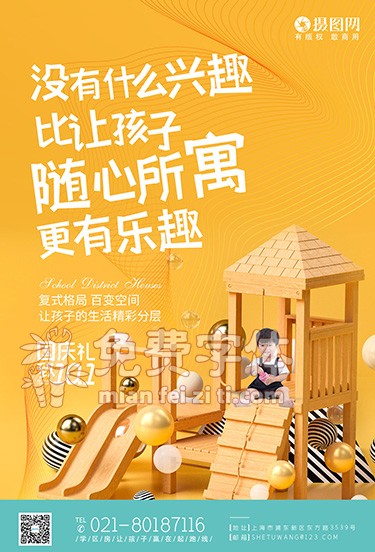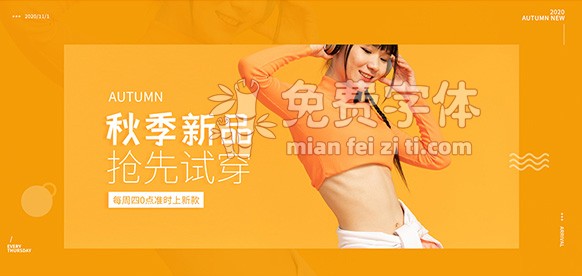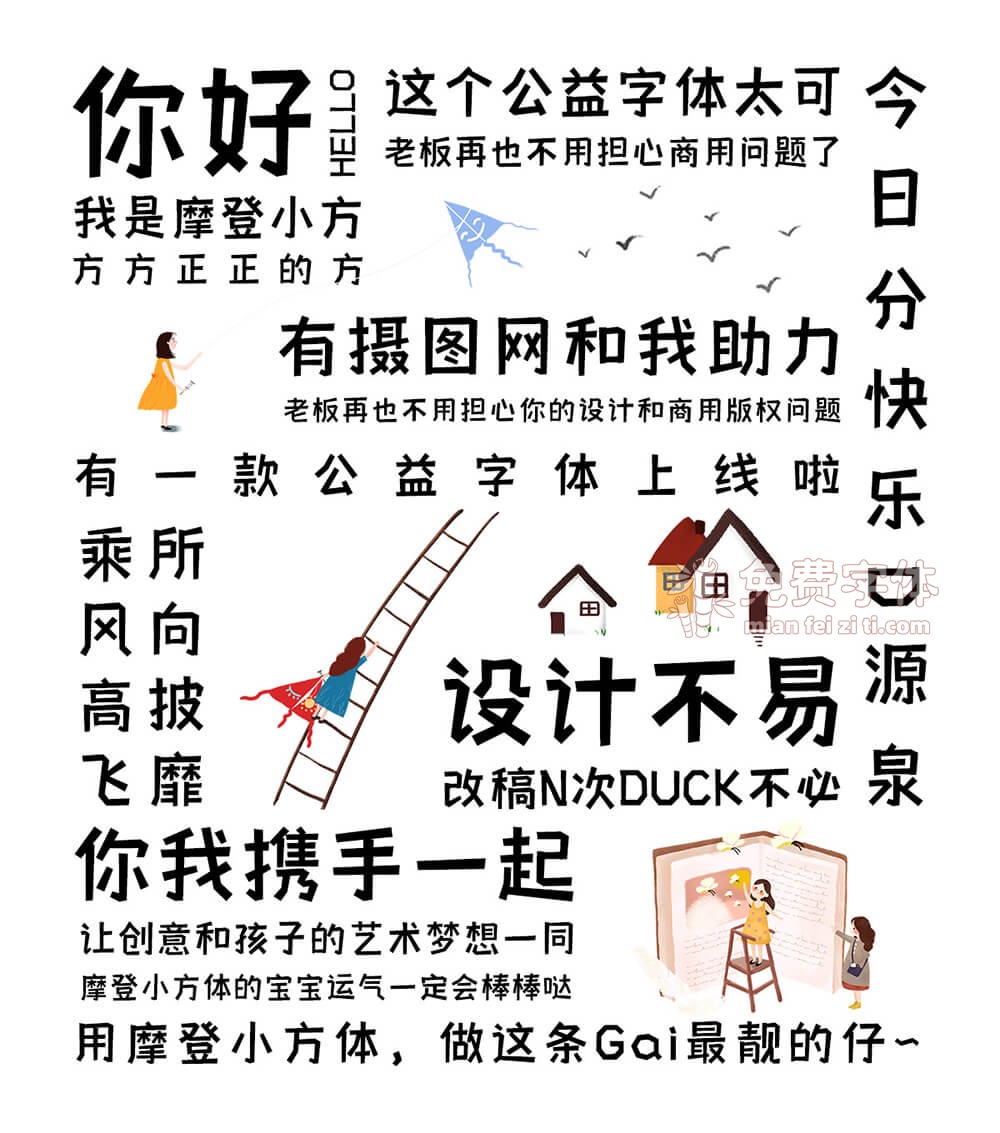
摄图摩登小方体是摄图网联合国内专业字体设计机构iFonts共同推出的一款公益创意黑体字。摄图摩登小方体作为一款创意黑体字,字体的设计灵感来自对未来空间的想象,传达给人一种未来与现实的交际感。笔画方正质朴而又不失灵气活力,适中的字体笔画粗度和几何感的细节设计,让字体有良好的视觉应用表现。
通过对字体负形空间的处理,使字体整体感觉稳重端正而又不呆板,更加具有趣味性。适合电商、广告、美食等商业宣传和包装设计,以及社交网络的个性化用字。